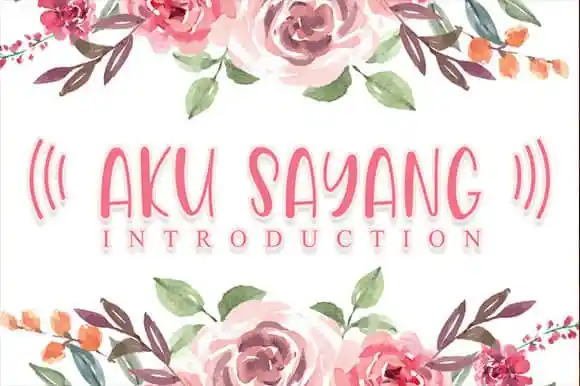
Aku Sayang Font – Download Grátis
Aku Sayang Font é uma elegante seleção de letras serif que traz personalidade para qualquer projeto. Perfeita para aplicativos em placas de parede, convites de casamento, logotipos de postagem social, anúncios e embalagens de produtos, esta fonte também encaixa-se perfeitamente nas criações de produto, rótulos, fotografia e mesmo no design dos créditos. Traz um toque especial, com sua elegância clássica, adequada para aqueles projetos que precisam de um gosto autêntico e delicado. Seja em uma viagem de carro ou numa festa ao ar livre, Aku Sayang é a fonte perfeita para destacar seu design único e singular. Sua simplicidade bela faz dela uma opção versátil e irresistível para qualquer iniciativa visual.